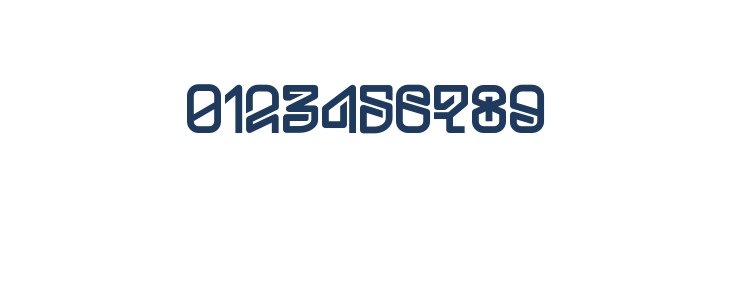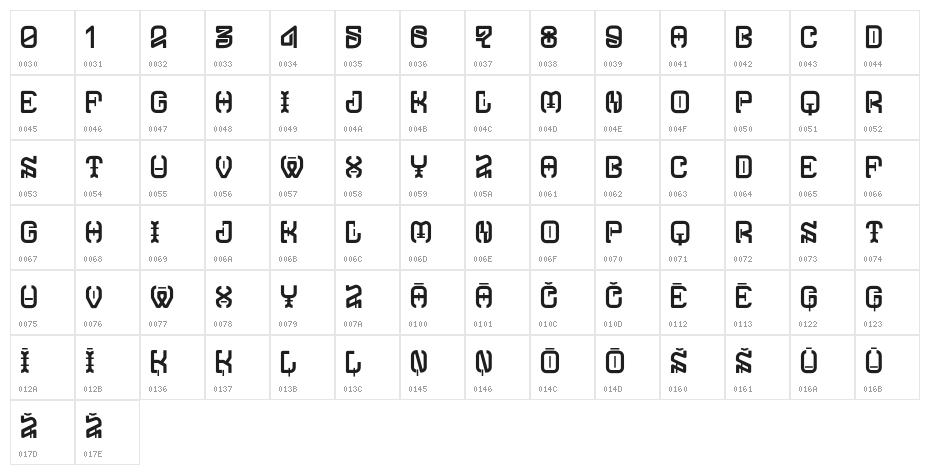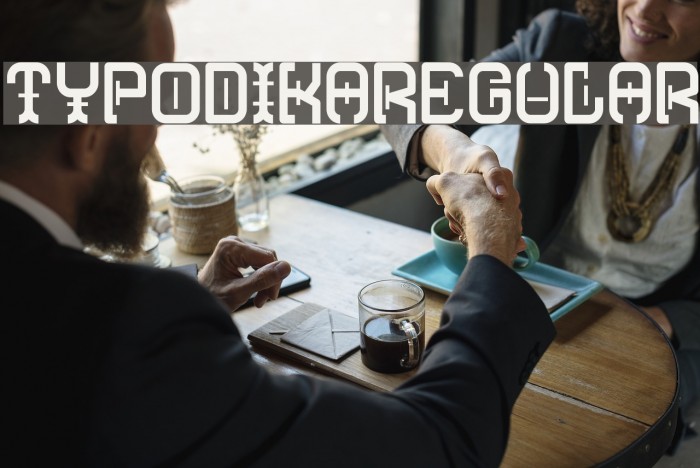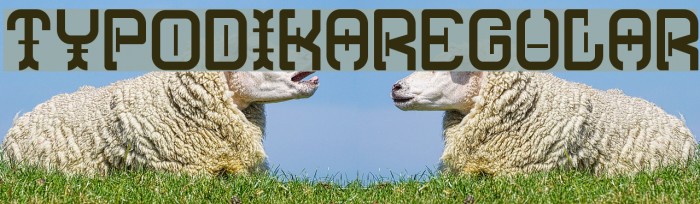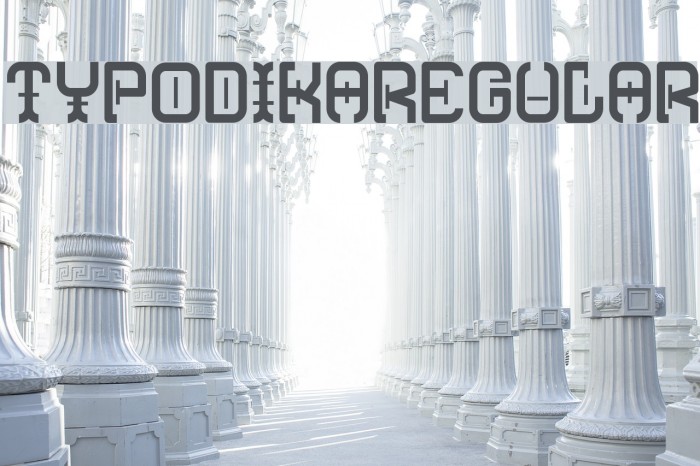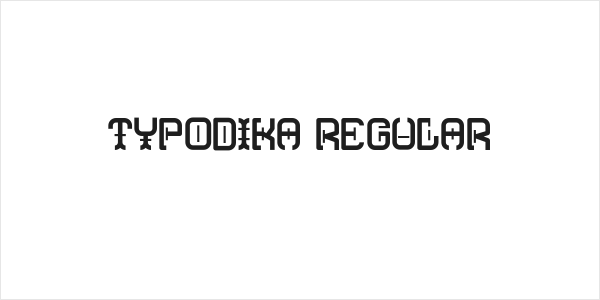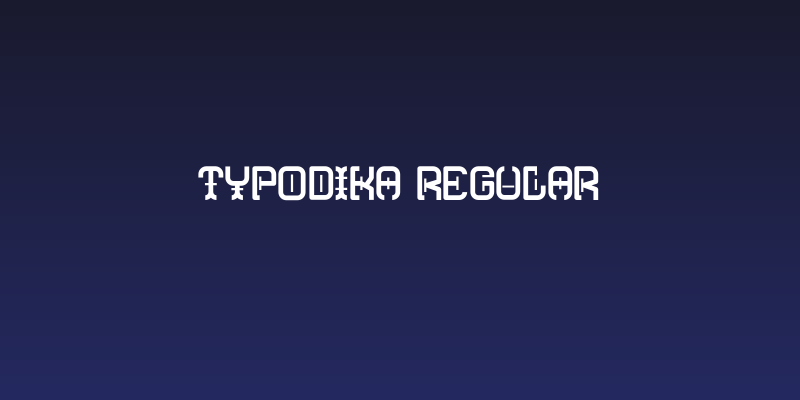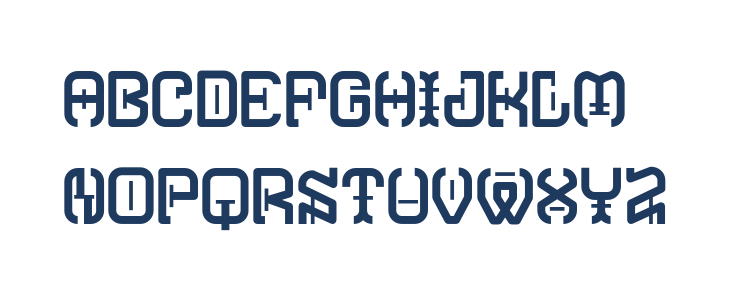
Typodika-Regular Font
Bolahool Graphics
| Progetti proposti | Perfect for branding, posters, album covers, and any project needing a modern, edgy look. |